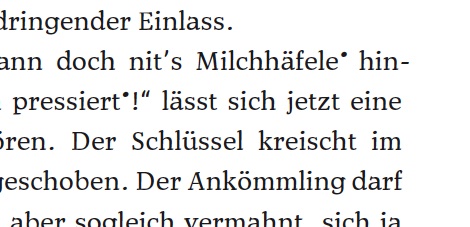
Ich sitze gerade an einem typografisch nicht ganz einfachen Buch und hab da mal ne Frage bzw. die Bitte um Anregungen. Es handelt sich um den Nachdruck eines Textes aus dem 19. Jahrhundert mitsamt seiner originalen Fußnoten. Diese originalen Fußnoten sind (wie im Original und deshalb muss es so bleiben) mit hochstehenden Sternchen im Text gekennzeichnet und werden im Textfluß am Ende des (originalen) Textabschnittes eingerückt im Fließtext gesetzt. Sternchen sind also vergeben. Daneben gibt es aber nun neue Fußnoten, die als Marginalien gesetzt werden und somit kein Zeichen brauchen. Dann gibt es aber zusätzlich noch neue Endnoten, die im Manuskript bisher durchnumeriert sind ...
Das Problem dabei ist, daß diese Endnoten, die im hinten liegenden Apparat des Buches abgedruckt werden sollen, durchgehend Personen oder Begriffe sind und im Apparat in alphabetischer Reihenfolge das Personenregister und das Begriffsregister bilden sollen. Weshalb eine Numerierung mehr Verwirrung als Hilfe stiftet und also nicht geht.
Weil aber nicht alle Namen oder Begriffe im Register auftauchen, würde ich schon gern im Fließtext an dem entsprechenden Wort ein Zeichen setzen, dass man dieses im Register findet. Der Klassiker diesbezüglich wäre eine Fußnote mit dem Text "siehe Register Seite sowieso". Das finde ich aber nicht schön, weil ich dann auf vielen Seiten teilweise sehr viele dieser häßlichen und immer gleichlautenden Fußnoten hätte. Die Generalisierung mit hochgestellten Sternchen geht auch nicht ... weil ja schon anders verwendet.
Was hättet Ihr an Vorschlägen für ein diskretes hochgestelltes Zeichen als Verweis "Zu diesem Wort/Namen findest Du was im Register" ? Falls das ne Rolle spielen sollte: ich setze aus der Ratio-Modern, also einer klassizistischen Antiqua. Das Ganze ist ein kulturhistorischer Text und eine gewisse Vornehmheit/Eleganz in der Gestaltung wird schon angestrebt. Also möglichst keine fetten Dreiecke oder Pfeile oder ähnliches aus der groben Didaktik-Ecke ...
Oder gibt es ein solches Zeichen womöglich schon?
klassisch und meines erachtens passend wäre ein hochgestelltes †, also schlicht so: ›name im register‹. von deinen kulturhistorisch beflissenen lesern kannst du dann ja auch erwarten, dass sie das nicht als ›verstorben‹ missverstehen.
aber noch etwas anderes, wenn du die einmischung gestattest:
ich setze aus der Ratio-Modern, also einer klassizistischen Antiqua.
findest du die ratio wirklich eine textschrift? ich mag mich täuschen, aber für typische lesegrößen erscheinen mir die haarstriche zu fein. ich hätte es, wenn es eine klassizistische sein soll, mit einer bodoni twelve oder, für die fußnoten, sogar einer bodoni six versucht.
von deinen kulturhistorisch beflissenen lesern kannst du dann ja auch erwarten, dass sie das nicht als ›verstorben‹ missverstehen.
Man könnte sowas ja von vorneherein ausschließen, griffe man stattdessen zum ‡ ...
Was hat das ‡ eigentlich für eine Bedeutung?
Ja, die Ratio funktioniert m.E. als Textschrift - ich hab recht viel Platz und damit genügend Durchschuß und sie kommt im Offsetdruck ganz ordentlich in 11p auf gelblich-weißem geglätteten Werkdruck. Die Bodonis mag ich nicht wirklich und außerdem soll es aus inhaltlichen Gründen eine deutsche klassizistische Schrift sein und die Walbaum - so schön sie auch ist - hab ich schon zu oft gesehen.
Ich finde, man darf dafür neue Zeichen erfinden. Raute, Kreis, Winkel, Dreieck …
In einem Jugendbuch habe ich das gleiche Problem mit einem etwas fetteren Punkt gelöst: „Dieses Wort ist im alphabetischen Register erklärt”
ein hochgestelltes †
ich dachte, wenn zu viele Sternchen auf einer Seite stehen, kommt dieses Kreuzzeichen zum Einsatz, danach das Kreuzzeichen mit zwei Querstrichen ...
Hab zwar lange kein solches Buch in den Händen gehabt, aber so war's wohl üblich.
Was hat das ‡ eigentlich für eine Bedeutung?
Hier sind einige Erklärungen zum †, die sich teils dann auch auf das ‡ beziehen.
Bedeutungen: wohl je nach Einsatzzweck
Die englische Version der Seite hat noch was mit Anmerkungen zu diskussions/anmerkungswürdigen Absätzen auf Lager: